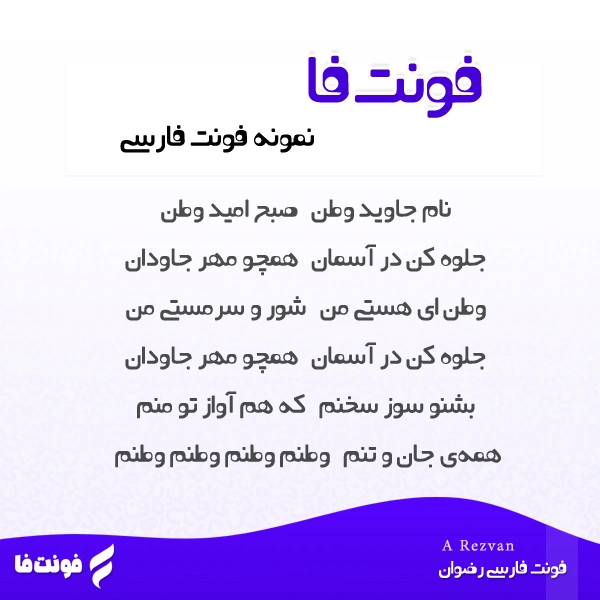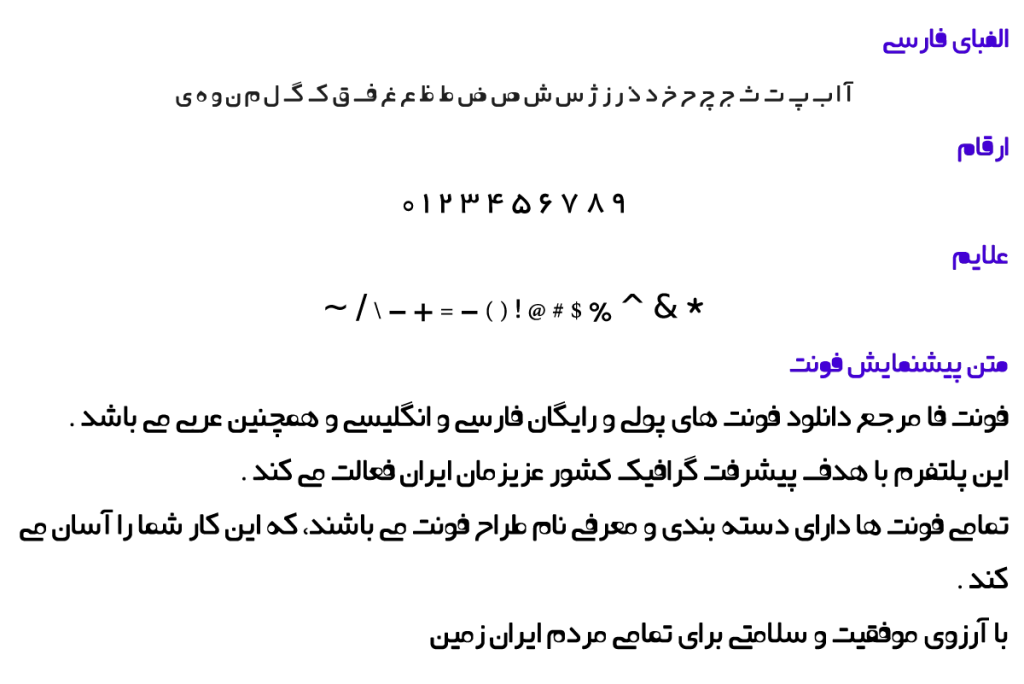
فونت فارسی رضوان - A Rezvan
توضیحات و معرفی فونت رضوان
فونت فارسی رضوان ( A Rezvan ) از مجموعه فونت های آزاد می باشد، همینطور نوع فونت گرافیکی می باشد.
فونت زیبای مرتبط توسط علی سواری طراحی و ساخته شده است.
قلم فوق با طراحی منحصر به فرد خود، ویژگی هایی مانند اعراب گذاری دقیق، تنظیم هوشمند فاصله بین حروف و وجود ده ها ترکیب حرفی را ارائه میکند.
این فونت از حروف و اعداد فارسی و عربی بطور کامل پشتیبانی می کند، حجم مناسبی دارد و در دو وزن مجزا پر و نرمال در دسترس است.
همینطور فونت A Rezvan در دو وزن پر رنگ و چاق است.
در لیست زیر می توانید وزن این فونت زیبا را ببینید.
• A Rezvan Bold
• A Rezvan Fat
در تصویر زیر، شعر کهن «وطنم» با این تایپ‌فیس به نمایش گذاشته شده است.